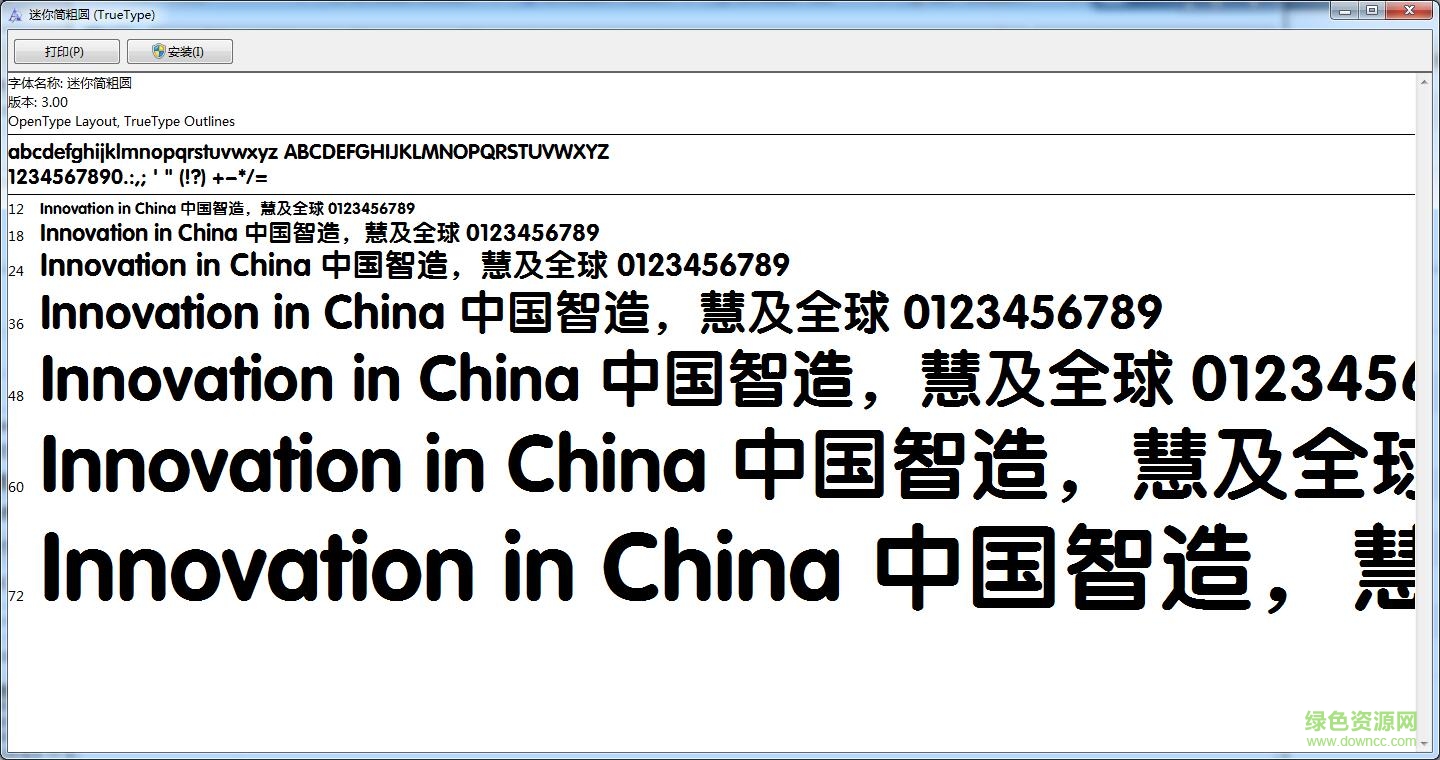
迷你简粗圆
迷你简粗圆字体是一款免费的中文字体。这个字体属于那种圆形的字体,做名片、公司设计logo的时候常常使用!非常的美观醒目,喜欢的用户可以免费下载!
字体介绍
迷你简粗圆是在粗圆字体的基础上开发的一款简体中文汉字,该字体粗细适中,大方得体,整体效果十分出色,并且字库完整,可以适用于名片设计、平面设计、广告设计、报纸杂志、企业LOGO、商标注册、电视台广告等领域!需要的用户欢迎来绿色资源网下载使用。
迷你简粗圆特点
1.粗细适中,大方得体
2.可以适用于名片设计、平面设计等行业领域